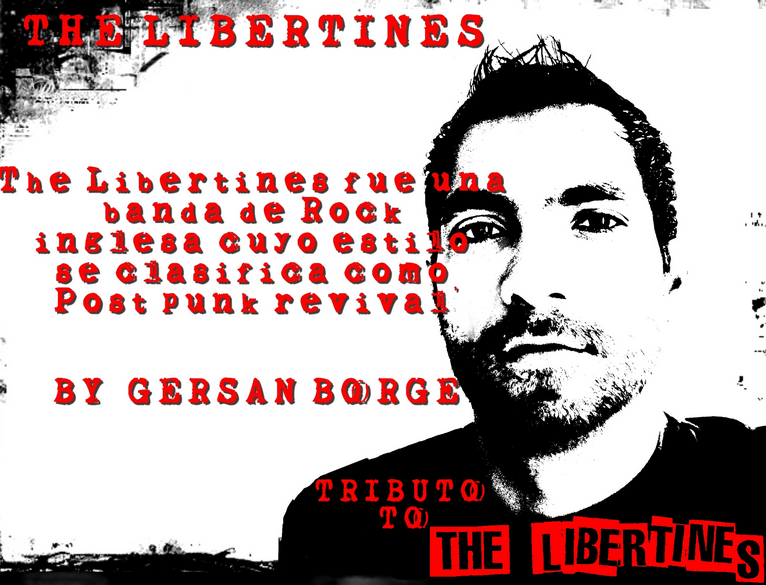
Font name: | The Libertines |
Author: | Gersan Borge A |
Note by Gersan Borge A | |
esta font fue creada con una maquina olimpia 2 y se la dedico a una de las mejores bandas de el genero post punk revival the libertines. |